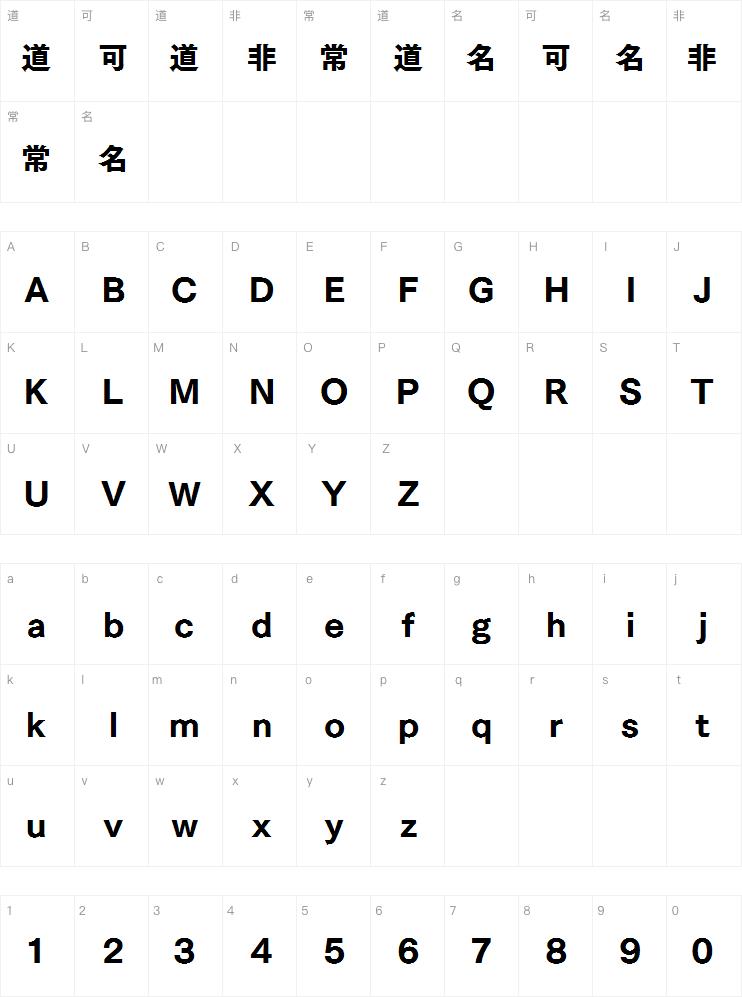
方正FW筑紫黑H
筑紫黑家族在设计上一直基于与2003年发布的筑紫宋体家族一致这一原则进行新的开发。使用范围广,包括书籍、杂志、目录、广告单等,重视文字的质感,保证要求品位时也可以满足要求。这是由八个字重组成的黑体家族系列,正文、解说词、小标题、大标题均设计为最佳表达方式。 筑紫黑体的书法风格将现代的鲜明感、洁净的坚硬感、经典的趣味以及柔和融为一体,既正统又给人新鲜感。在重视现代字体设计的主流“均质性和均匀性”的同时,又不忘记“文字是边用手写边设计形成的”这一点,与筑紫宋体同样地使“写”这一手的动作坦率地表现在文字中。能看出“写”这一动作,是基本字体的使命“鲜明地突出文章的含义”这一表现力的源泉。在建立、使用和阅读字体的各个行为中重新验证了可以表现现代世界的黑体的使命和作用,这是设计的根本,筑紫黑体就是在对这个根本的重新审视中产生的。